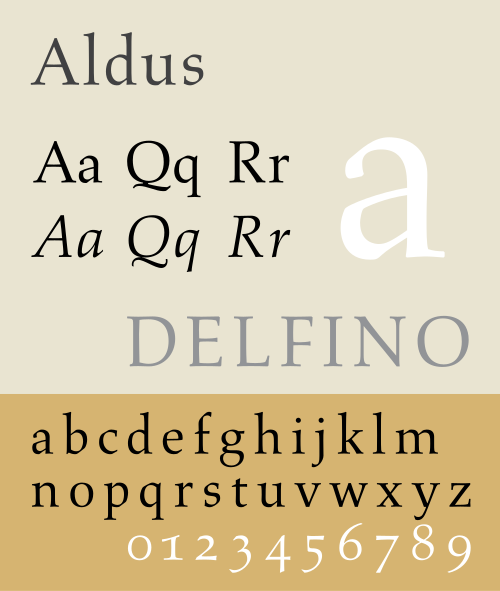
| カテゴリ | セリフ |
| 分類 | 旧式 |
| デザイナー | ヘルマン・ツァップ |
| 鋳造所 | ステンペル ライノタイプ |
| 作成日 | 1948 |
| リリース日 | 1949 |
| バリエーション | パラティーノ ノヴァ パラティーノ サンズ |
パラティーノは、ヘルマン・ツァップがデザインした古いスタイルの セリフ 体書体で、1949年にステンペル鋳造所から最初にリリースされ、後に他の企業、特にメルゲンターラー・リノタイプ社によってもリリースされました。[a]パラティーノは、オープンカウンター、バランスの取れた比率、適度なストロークのコントラスト、広がったセリフ により、読みやすさが最適化されています。
背景
16世紀イタリアの書道の巨匠、 ジャンバッティスタ・パラティーノにちなんで名付けられたパラティーノは、イタリアルネッサンスのヒューマニズム書体に基づいており、太いペン先で書かれた文字を模倣しており、書家としてのツァップの専門性を反映している。[4]大文字の「Y」は、ギリシャ文字のウプシロンに触発された珍しい「手のひらのY」スタイルで、アルドゥス・マヌティウスの書体など、この文字の最も初期のバージョンのいくつかに見られる特徴である。[5]
ルネッサンス期に復活した書体のほとんどが、低いエックスハイト(小文字が短く、アセンダとディセンダが長い)などの繊細な比率になっているのに対し、パラティーノは比率が大きく、可読性が向上している。[6] [7]パラティーノは、見出し、広告、ディスプレイ印刷などの商業用または「ジョブ」用のデザインとして特に意図されており、離れて読んだり、小さなサイズで印刷した場合でも、低品質の紙にはっきりと見えるように、しっかりとした幅広の構造と広い開口部で作成されました。
パラティーノは、ステンペルが「拡張ファミリー」として売り出した、ツァップによるいくつかの関連書体のうちの1つである。[8]このグループには、パラティーノ、システィーナ、ミケランジェロ、アルドゥスが含まれる。ツァップの伝記作家ジェリー・ケリーは、これらを「当時の古典的なルネッサンス形式に基づいた最大の書体ファミリー」と表現している。[9] [10] [11]これらのデザインは、イタリアのルネッサンスの文字形式とローマの角張った大文字に強く影響を受けているが、ツァップはパラティーノ・ローマンを完成させるまでイタリアを訪れることができなかった。[12] [13]パラティーノは急速に本文での使用で人気が高まり、ツァップがこの用途のためにデザインした、より細く軽いアルドゥスを凌駕した。最も使用されているセリフ書体のトップ10に数えられている。[13] [14]パラティーノはもともと本文用にデザインされたものではないため、一部の文字は風変わりなカリグラフィのデザインで目立つように意図されていましたが、後にツァップはより落ち着いた代替文字で再デザインし、これがほとんどのデジタル版の標準となりました。[13] [15]
Linotype は Palatino のライセンスを Adobe と Apple に供与し、両社はそれを標準フォントとしてPostScriptデジタル印刷技術に組み込みました。これにより Palatino はデジタルおよびデスクトップ パブリッシングでの重要性が保証され、ほとんどのコンピュータに (またはその派生版が) プリインストールされたフォントとなりました。多くの人気フォントと同様に、模倣デザインや別の名前での再リリースはよくあります。Zapf はデザインへの関心を持ち続け、80 代になっても新しいバージョンの作成に協力し続けました。
パラティーノ家
パラティーノ
パラティーノ自体は、前述のように、質の悪い紙や印刷物でも明瞭に読めるよう、しっかりとした構造になっている。ツァップの友人であるアレクサンダー・ローソンは、「パラティーノの読みやすい文字にしているオープンカウンターは、当時のドイツにおける印刷の問題、つまり質の悪い紙を克服するために用意された。活字の厚みも、当時の石版印刷やグラビア印刷のプロセスに適応するため、通常のローマン体よりも厚くなっている。ツァップは、パラティーノを書籍の活字としてではなく、商業用の書体として作ったと一貫して主張している。」と書いている。[13] [16]
パラティーノは本文で人気が高まったため、手作業による植字、溶製金属植字、写真植字、デジタルフォントデザインといった技術の変化に合わせて複数のバージョンがリリースされた。後のバージョンでは、't' が下がったり、'p' と 'q' にフットセリフが付けられたりするなど、細部が規則的になっていることが多い。[13]特にイタリック体は何度か再設計されており、手作業による鋳造活字のオリジナルは明らかに細く、ライノタイプ機用はローマン体との二重印刷を可能にするために明らかに幅が広く、その後の写真植字とデジタル技術用のバージョンは両極端の中間となっている。ハットナーとケリーはパラティーノを「明らかに現代的...特定の初期モデルからコピーされたものではない現代的な書体」と評している。[17]
パラティーノの金属活字のイタリック体には、スワッシュ大文字のセットが含まれていた。これらはデジタル化では発見されていないが、ツァップのルネッサンス・アンティクア・デザイン(後述)のデジタル化には(わずかに異なる)セットが含まれている。[18]後のバージョンでは多くの文字のディセンダーが変更されている。ツァップは当初、ブラックレター書体に最適化されたドイツの共通線規格に合わせるために、これらを短くする必要があったが、後のバージョンではこの制限がなくなった。[19]
アルダス
| カテゴリ | セリフ |
| 分類 | 古いスタイル |
| デザイナー | ヘルマン・ツァップ |
| 鋳造所 | ライノタイプ |
| 作成日 | 1954 |
| 商標 | ライノタイプ |
アルダスは古いスタイルのセリフ体デザインで、書籍印刷でよく使われています。数年前にリリースされたパラティーノと比較すると、より凝縮されたデザインで色が薄く、より優雅で洗練されており、平均的に質の高い書籍印刷に適しています。[13] [20]アルダスはカーニングのない ローマン体とイタリック体の fを備えているため、タイポグラファーは合字を使わずに済みます。1954年にD.ステンペルAGのカタログに掲載され、ツァップは文字デザインの歴史を記した自身のManuale Typographicumに使用しました。[21]
アルダスは、ヴェネツィア・ルネサンス期の印刷業者アルダス・マヌティウスにちなんで名付けられた。この決定は、アルダスの書体とほとんど類似していないため、ツァップ(「パラティーノ・ブック」という名前を好んだ)を怒らせた。[13] [22]
Palatinoと同様に、アップグレードされたデジタル化であるAldus NovaがLinotype社からリリースされました。[23]
ミケランジェロ
ローマの角柱大文字をベースにしたタイトル用大文字のセット。デザインは右下にフットセリフ付きの「U」、上部に4つの終端を持つ「ダブルV」スタイルの「W」、そしてギリシャ文字のウプシロンに触発されたパラティーノのものに似た「手のひらY」です。 [ 13]名称の権利をデジタル化も出版したベルトルドが保有していたため、パラティーノ・ノヴァ・リリース(下記参照)で「パラティーノ・タイトル」に改名されました。[24] [25]
システィーナ
ミケランジェロと同じ基本構造で、タイトル用大文字のセットよりもわずかに太い。[13] [26] [27]元々はローマ街道のアウレリア通りにちなんで「アウレリア タイトル」と名付けられていたが、後にツァップは別のフォントにその名前を使用した。[28]パラティーノ ノヴァ バージョン (下記参照) は「パラティーノ インペリアル」に改名され、小文字が小文字になっている。[29] [30] [31]これは、ツァップがそれまで訪問できなかったイタリアへの芸術的に生産的な 1950 年の訪問の後に作成された。[32]ツァップはイタリアの芸術とレタリングの質に非常に興味を持っており、フィレンツェの石彫刻のスケッチは、人文主義的なサンセリフ体 Optimaにも影響を与えた。[33] [34] [35]
コンパクト
非常に太字の表示書体で、わずかに傾斜しているが、イタリック体ではなくローマン体の文字形式である。[36] [37]パラティーノとは異なり、太字を使用しなかったルネッサンス時代のローマン体印刷のスタイルとは非常に異なっている。
ツァップ ルネッサンス アンティカ (1984–1986)
Zapf Renaissance Antiqua は、Stempel の金属製 Palatino ファミリーの一部ではありませんが、1984 年から 1986 年にかけての同じ Renaissance モデルの Zapf による別の解釈です。最初は Scangraphic 向けに作成され、後に Linotype によってデジタル化され、Palatino と共に販売されました。Palatino と比較すると、Zapf Renaissance Antiqua は、鋭いセリフやくさび形の句読点にまで引き継がれるストロークのコントラストが高く、太いストロークと細いストロークの間の遷移も滑らかです。[38]また、各小文字に 5 種類ものバリエーションを含むスワッシュ レターフォームの完全なセットが含まれていることでも有名ですが、これは Palatino のデジタル バージョンには含まれていません。[39] [38] Linotype によると、現在利用可能なデジタル化は Scangraphic がディスプレイ用に準備したバージョンに基づいており、間隔が狭く、ストロークの太さのコントラストが際立っています。 「Zapf Renaissance Antiqua SB」という名前で販売されているバージョンには、同じ高コントラストの文字が含まれていますが、本文の間隔はより緩やかになっています。しかし、一部のタイポグラファーは、入手可能なすべてのデジタル化の間隔の品質が悪いと批判し、元の独自のデジタル形式からPostScriptへの変換が不正確であると述べています。[38]
Palatino の初期のデジタル化は PostScript での使用を意図しており、広く使用または複製されている。その後の Palatino デジタル化では、機能や間隔が異なっている。1999 年に Zapf は Linotype とMicrosoft向けに Palatino を改訂し、Palatino Linotype とした。改訂されたファミリーには、拡張されたラテン文字、ギリシャ文字、キリル文字セットが組み込まれた。Linotype は、Zapf の他のルネッサンス風デザインや Aldus のデジタル化とともに、より複雑な再設計である Palatino nova をリリースした。Zapf は 2006 年に、それと一致する Palatino Sans と Palatino Sans Informal デザインも作成した。[40]
パラティーノ・ライノタイプ
Palatino Linotype は、Microsoft ソフトウェアの最新バージョンに含まれる Palatino ファミリのバージョンです。拡張ラテン文字、ギリシャ文字、キリル文字、通貨記号、下付き文字と上付き文字、分数が組み込まれています。ファミリには、テキストのローマン体とイタリック体、太字が含まれます。
Palatino Linotype は、マイクロソフトが出荷した最初の西洋OpenTypeフォントとして有名で、 Windows 2000にバンドルされていました。OpenType バージョンでは、合字、真のスモールキャップ、プロポーショナル数字と表形式の数字、テキスト数字、スワッシュ大文字 Qu の組み合わせなどのさまざまな特殊な代替文字を含む、いくつかの (当時の新しい) 代替機能が紹介されました。[41]これは、 ThやQuなどの合字を含まないOS Xシステムバージョンなどの以前のデジタル化とは一線を画しています。リリース時には、感嘆符を組み込んだ数少ないフォントの 1 つでした。[42]